在搜索框里输入「Minecraft 字体」,你会得到两批互相矛盾的结果。一批给你一款扁平的像素字体,另一批给你布满裂纹的厚重石块字母。两批都自称是我的世界的字体。
两批都没错,因为我的世界用的是两种完全不同的字体,而游戏本身只附带其中一种。几乎所有搜索的人,心里想的都是第二种。
简短的答案:是两种字体,不是一种
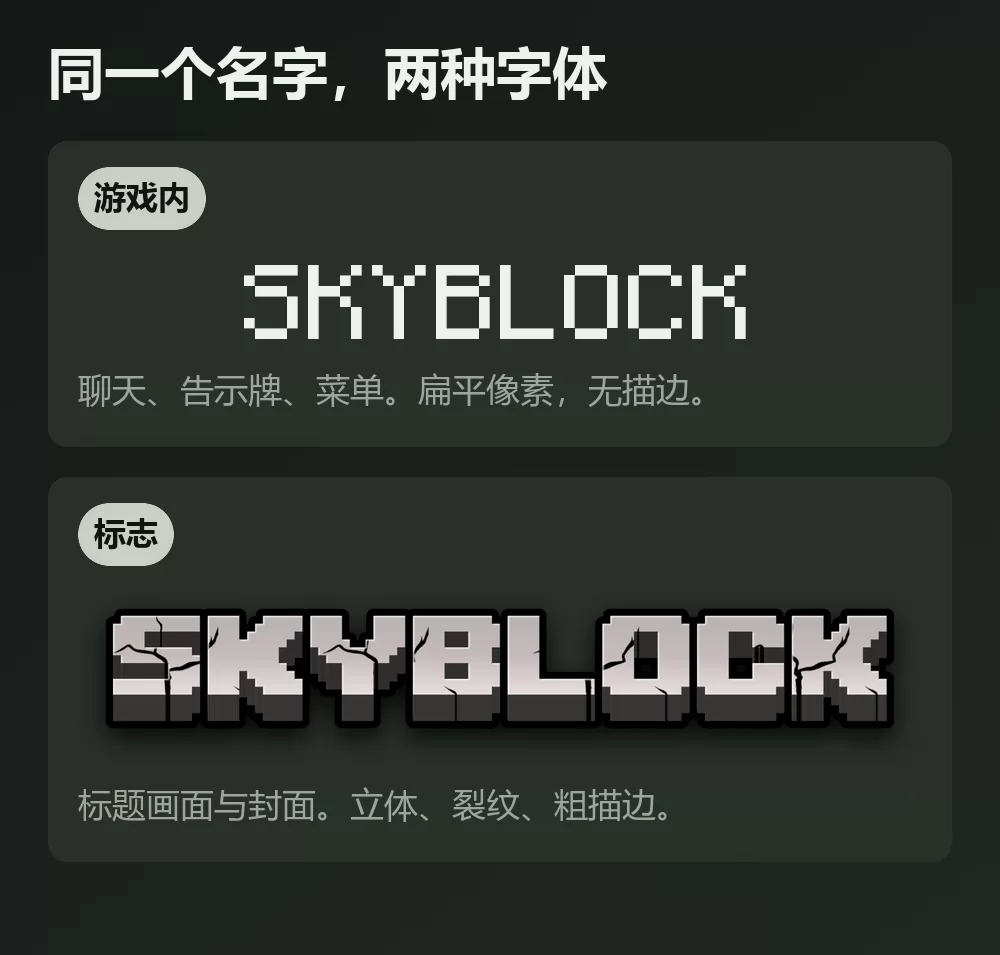
Mojangles 是驱动游戏的那一种。聊天、物品名称、告示牌、菜单,以及所有你眯着眼睛看过的计分板,用的都是这款小小的像素字体。扁平,没有明暗,没有描边。
标志用的那一种,是标题画面和包装盒上那种雕刻在石头里的厚重字体。它有立体感、粗重的深色描边,字母上还有贯穿的裂纹。它在游戏里根本不作为字体存在:它是一幅美术图。
如果你要做服务器横幅、YouTube 封面、SMP 标志或 Discord 页眉,你要的是第二种。如果你要复原一条聊天记录或一块告示牌,你要的是第一种。
Mojangles 究竟从哪里来
这一段是真正值得一提的冷知识,而大多数页面都写错了。
Mojangles 比我的世界还早。马库斯·佩尔松在 2001 年为自己更早的一款游戏 Legend of the Chambered 画了它,比我的世界的问世早了八年,而它的依据是 1984 年 IBM EGA 显卡内置的 8 x 8 像素字体。这款你与史上销量最高的游戏联系在一起的字体,最初是早期 PC 显卡的硬件字符集。
顺带纠正一处,因为到处都写着相反的说法:Mojangles 不是等宽字体。 它的字形画在 8 像素的网格上,但宽度从 1 像素到 8 像素不等,所以大写 M 占的位置远比小写 i 多。好几篇流传很广的指南说法正相反。打开任意一个我的世界存档看一块告示牌,两秒就能验证。
Monocraft,授权干净的那一款
如果你想要游戏内的观感又想睡得安稳,答案就是它。Idrees Hassan 的 Monocraft 是一款受我的世界界面字体启发的等宽字体,以 SIL Open Font License 1.1 发布。也就是说:自由使用,包括商业用途,注明来源即可。
它也是其中最完整的一款:1500 多个字形,覆盖带附加符号的拉丁字母、西里尔字母和希腊字母,还包括附魔台上的标准银河字母。提供 .ttf 与 .ttc 两种格式,作者明确说明这是一个不含任何 Mojang 素材的粉丝项目。
有两点要知道。它是刻意做成等宽的,与 Mojangles 不同,因为它本是作为编程字体设计的,所以长单词看上去会比游戏里稍宽一些。另外它没有中文、日文和韩文字形,如果你本打算用它排中日韩文字,这一点很关键。
免费的像素复刻版
下载量最高的那款就直接叫「Minecraft」,作者是 Craftron Gaming,在 DaFont 上接近五百万次下载。它是一个 6 KB 的 TrueType 文件,重现了游戏内那种扁平的观感,DaFont 标注它 100 % 免费。
MineCrafter,标志的那一款,以及大家都漏看的授权
Madpixel Designs 的 MineCrafter 就是标志上那种石刻字体,还带一个裂纹变体。它被下载了约 475 万次,也是大多数人最终真正安装的那一款,因为那正是他们脑中想要的效果。
游戏实际加载了什么,逐个版本来看
如果你是为了准确而不是为了下载而来,这套字体组合比「我的世界用 Mojangles」有意思得多。
Java 版默认加载四款字体:
- Mojangles,用于游戏内几乎全部文字。
- GNU Unifont,一旦文字中出现 Mojangles 没有字形的字符,就由它接手。
- Standard Galactic Alphabet,附魔台上的符文字体。
- Illageralt,正常游玩中不使用,但可以通过命令调出。
基岩版加载六款,额外加入用于 Marketplace 内容等较长文本的 Noto Sans,以及用于菜单标题的 Minecraft Ten。基岩版还允许在聊天设置里把聊天字体在 Mojangles 与 Noto Sans 之间切换,这是游戏唯一一处给你字体选项的地方。
这种回退到 Unifont 的机制,解释了玩家常常注意到的一个现象:用 Mojangles 不覆盖的语言打字,字母形状会在句子中途变样。没有任何东西坏掉。游戏只是悄悄换了字体,因为前一款没有对应的字符了。
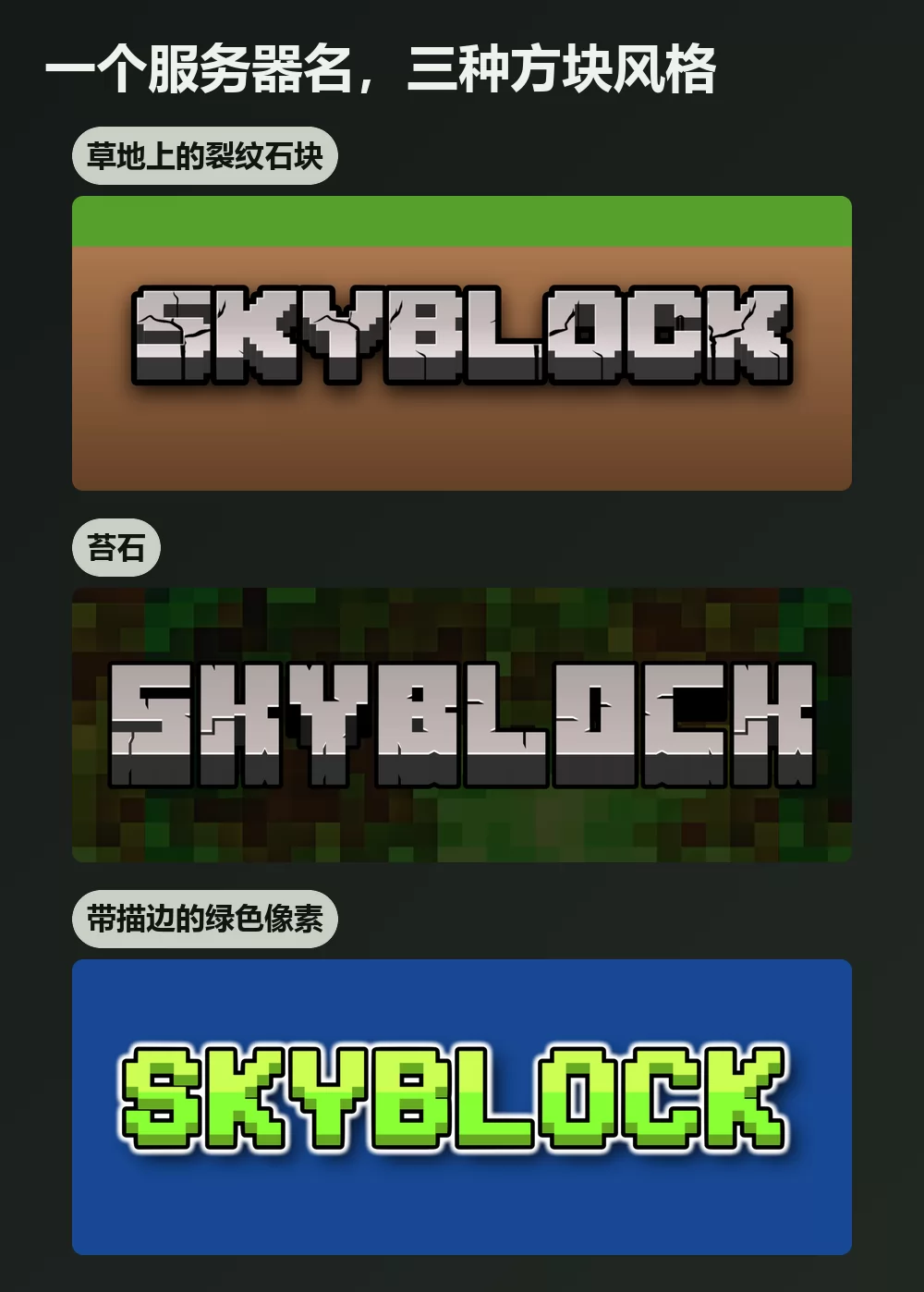
常见问题
我的世界的聊天和告示牌用什么字体? Mojangles,一款 8 像素的点阵字体,由马库斯·佩尔松在 2001 年绘制,源自 IBM EGA 的字符集。它不以字体文件的形式发布。
我的世界标志用的是什么字体? 是定制美术图,而不是发布过的字体。大家都在用的复刻版是 Madpixel Designs 的 MineCrafter,属于 donationware,仅个人使用免费。
有没有可以商用的免费我的世界字体? Monocraft,采用 SIL Open Font License 1.1。它是界面字体的粉丝复刻,不是标志字体,覆盖拉丁字母、西里尔字母和希腊字母。
为什么我的世界的文字在某些语言里会变形? 因为 Mojangles 没有那些字符的字形,游戏会回退到 GNU Unifont。这是预期行为,不是故障。